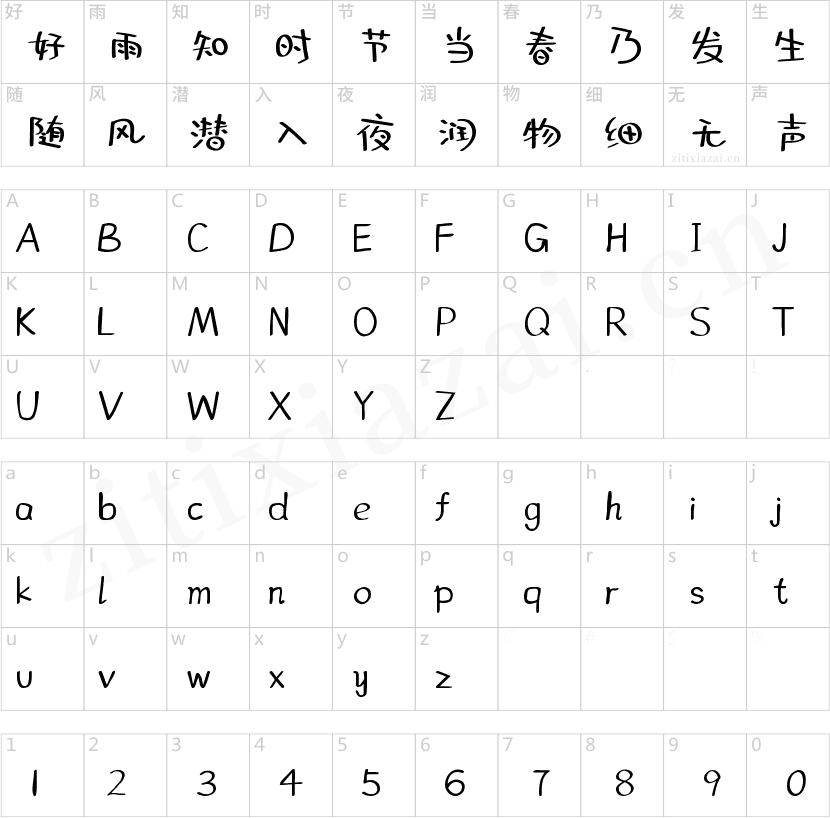
字魂113号-呆萌少女体
字魂字体字小魂呆萌少女体字体是由字魂创意字库设计并生产的一款可商用的字体,被收录于字小魂系列。该字体支持GB-2312标准,包含6763个中文、字母、符号和数字,字体类型偏向硬笔手写,具有活泼、动漫、可爱、时尚、圆润的风格,在市面上广泛用于广告电商、运动户外、晚会年会等场景。